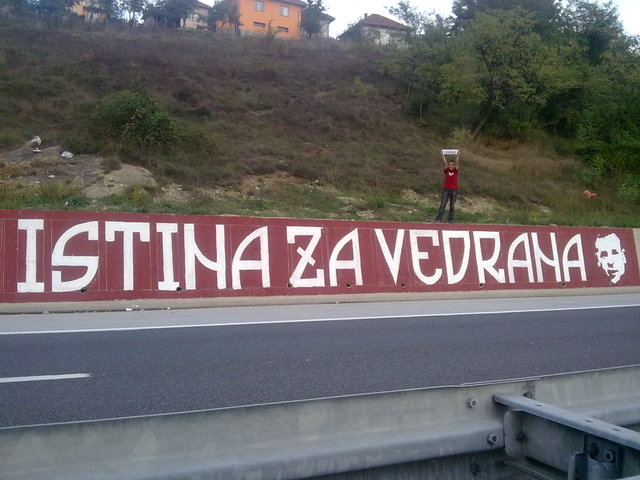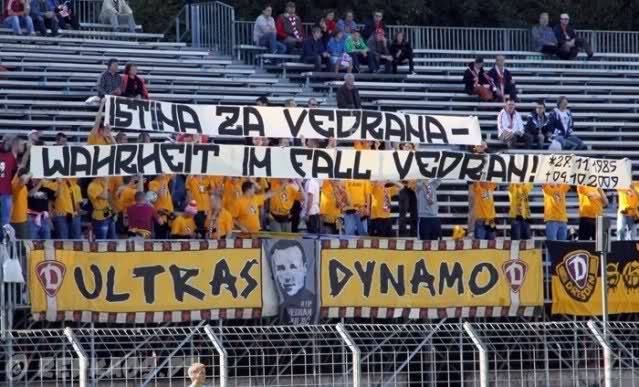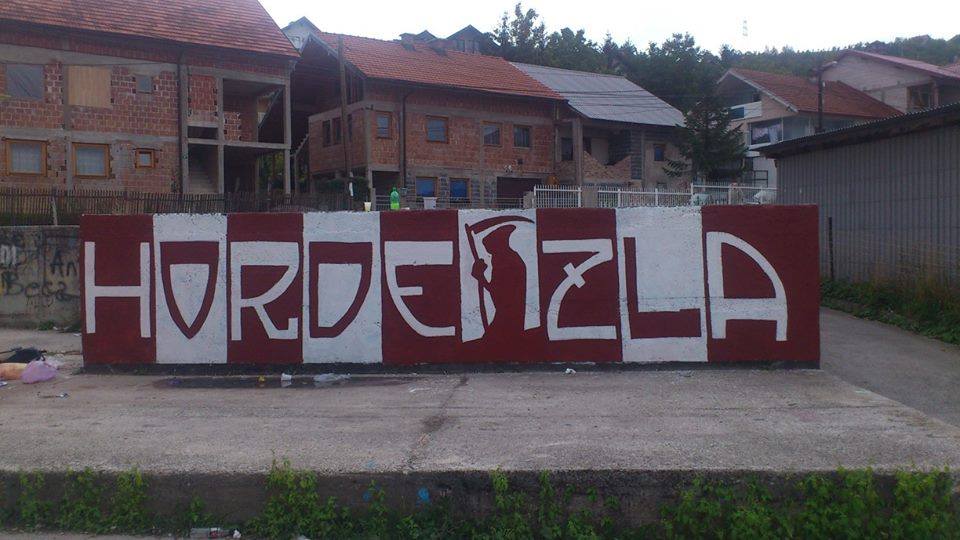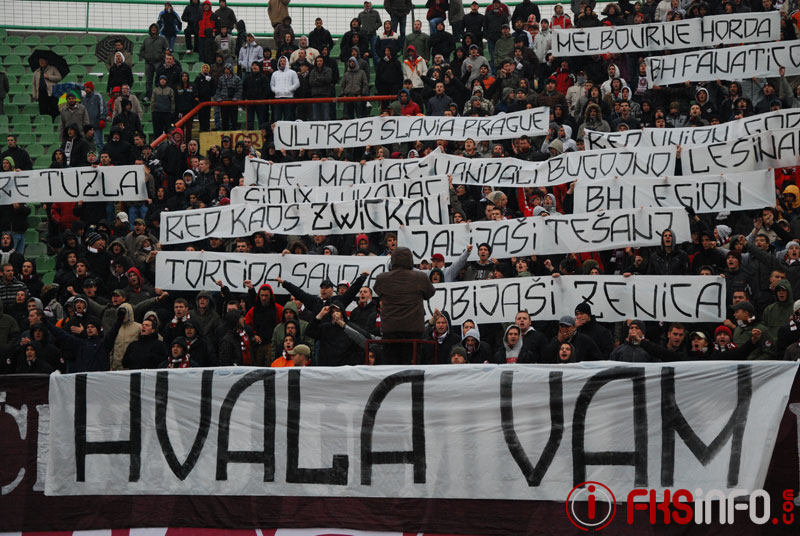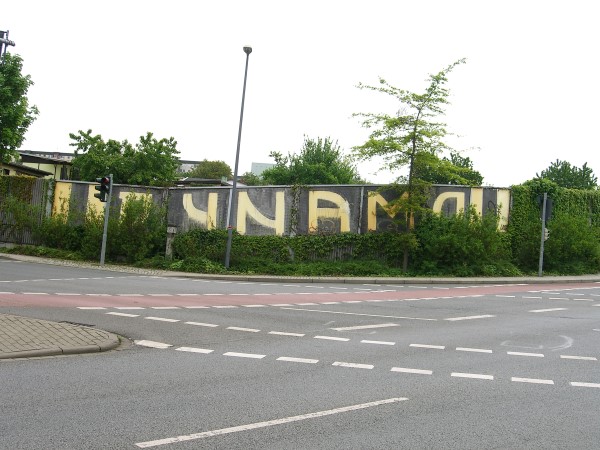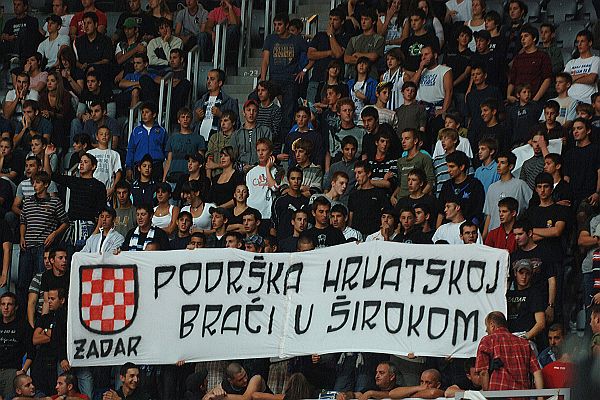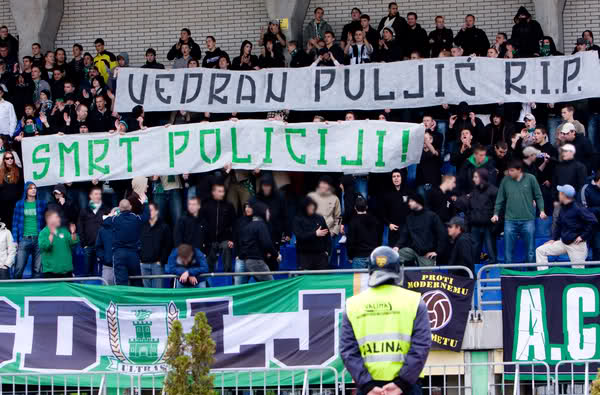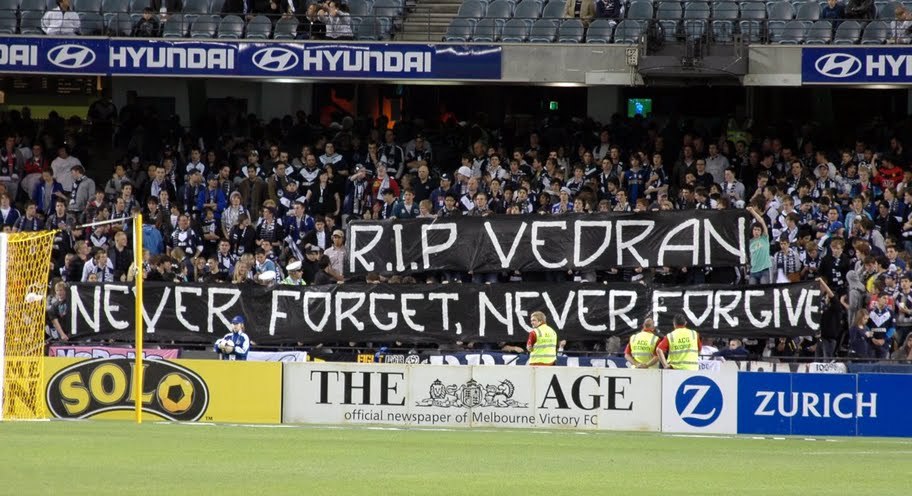
Kennt jemand diese „komische Fußball-Schrift“ ?
Mir fällt manchmal bei paar Grafittis in der Stadt eine Schrift ins Auge, die ich irgendwie interessant finde. Jetzt habe ich mal geschaut und habe die aus irgend einem Grund bisher eigentlich immer nur im Zusammenhang mit Fußball- und entsprechenden Fan-Vereinen gefunden.
Habe mal ein paar Bilder zusammengesucht.
Ist das eine bekannte Schrift? Oder irgendwie eine Art Szene-Eigenerfindung? Sieht auch irgendwie bisschen „nordisch-runenhaft“ aus … ich tappe grade echt im Dunkeln.
Irgend eine Idee?
Tradizione Regular! Ist nix Runisch sondern Italienisch aus dem Anfang des 20ten Jahrhundert?
Tradizione Regular auf Abstractfonts: *link entfernt*
Auf DaFont findet man die Schrift als Ultras Liberi: *link entfernt*
Weiß jemand noch was genaueres über die Schrift?
Hat die irgendwas mit ner Fußball-Tradition oder Ultra-Fans zu tun? o.0
Sehr spekulativ aber dennoch:
Die Tatsache, dass „Brusa“ sich mit „brenne“ übersetzen lässt (norditalienischer Dialekt) …
die Schrift eine starke Verbreitung in der italienischen Ultras-Szene findet …
und die Symbolik der paar dingbats in dem font (siehe die Version auf abstractfonts) …
verheissen allesamt nichts Gutes.
der rechtsradikale Hintergrund des Erstellers des Font war nicht zu übersehen. Viele faschistische Zentren in Italien benutzen diese Schrift. Aber ich habe auf die Charakterfestigkeit der hier Anwesenden vertraut und keinerlei Wertung vorgenommen. Diese Schrift haben auch Ultras von St Pauli verwendet, welchen man defintiv keine Sympathie von rechtsradikalem und faschistischem Gedankenungut vorwerfen kann. Nach meinem Wissen sind Schriften dieser Art, geometrisierte Art-Nouveau-Schriften, irgend wann mal in den 1920ern (Schwerpunkt in Italien?) aufgetaucht. Viel mehr habe ich aber nicht in Erfahrung bringen können.
Ich musste ja jetzt ganz schön suchen, wo denn hier in den Glyphen die Swastika und das Symbol der Totenkopf-SS sein sollen … so wie’s aussieht existieren mehrere Versionen der „Tradizione“ und nur die Version „1.00 1“ bei abstactfonts ist derart, äh … „komisch“. Die anderen (z.b. bei dafont) sind ja mehr oder weniger „clean“.
Ich war auch heute extra mal im Fanhaus von Dynamo Dresden. ^^ (Ich hätte mal nie gedacht, dass ich jemals da hingehe. Was doch die Typografie alles so bewerkstelligt … ;) ) Dort brachte jemand diese Schrift ebenfalls mit der Ultra-Fanszene, Italien und den 1950ern in Verbindung. Mehr wusste da niemand. Darauf angesprochen, ob da irgendwie „rechtsextreme Hintergründe“ damit verbunden sein könnten, besonders weil eben ein Font auffindbar ist, der diverse Glyphen beinhaltet: völliges Unverständis, ist für ihn nicht nachvollziehbar gewesen.
Also etwas ein Mysterium ist es schon. Mal sehen, was ich noch so recherchieren kann.
Viele faschistische Zentren in Italien benutzen diese Schrift.
Quelle, Beweis, Foto, etc? Wer hat diese Aussage getroffen und wieso; oder wie ist es zu dieser Annahme (deinerseits?) gekommen? (Was sind im Übrigen „faschistische Zentren“, mal so ganz dumm gefragt? Sowas hier? ^^)
Hat das wesentlich interessantere „O“ – ist aber leider zur Hälfte hinter der Hecke versteckt. Man kann sichs aber (da spiegelsymmetrisch) ganz gut zusammenreimen. ;)
Nenene, ich meinte eher die anderen Faschisten aus der völkischen/nationalen Ecke. Da wurde die Schrifte des öfteren auf den Fassaden verwendet. Bilder habe ich gelegentlich gesehen, aber kann keine Links nachreichen. Vmtl. die die Verbindung zu Hulligans die Ursache für die Verwendung. Das war IIRC die Ecke der autonomen Nationalisten. Ich habe da aber nicht so genau hingesehen, bei der Dokumentation ging es um andere Dinge. Da diese Bilder in einem ganz anderen Kontext aufgetauchts sind wird es sehr schwer zu suchen.